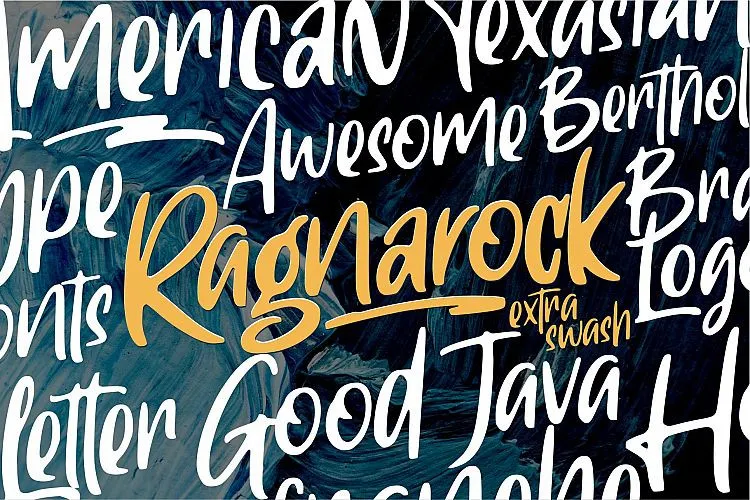
Descubra Ragnarock Script Font, uma nova opção para designers criativos no Brasil. Esta moderna fonte script apresenta um estilo robusto e descontraído que certamente encaixará perfeitamente em vários projetos de design. Introduzida pela Good Java Studio, a Ragnrock traz diferentes swashes e alternativas de letras para complementar qualquer projeto. Através da Ragnarock Font, os designers têm à disposição muitas opções para aumentar o impacto visual em diversos formatos de mídia. Isso inclui posters, logotipos, marcas de marca, rótulos, citações, títulos de perfil, bandeiras e camisetas design, embalagens, revistas, brochuras e muitos outros projetos incríveis. Seja para criar sua nova identidade visual ou apenas tornar o seu trabalho mais atraente e profissional, essa fonte é uma excelente escolha.